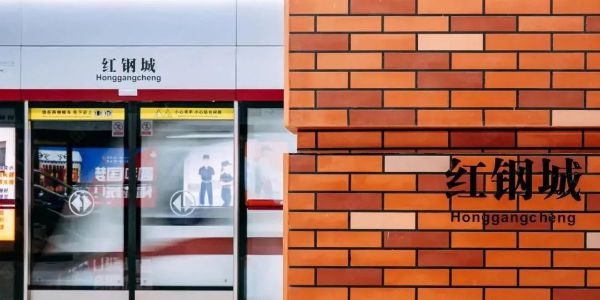
当地铁遇上宋体=铁宋
地铁,很多人每日出行的必备交通工具;宋体,生活中最常见的字体之一,然而它们的组合却不多见。但也正因为少,当地铁遇上宋体,反而就更加容易产生非常具有辨识度的效果。
如果到访过香港,乘搭过MTR,就很难不留意到各色磁砖墙、书法壁、标志性的「出」等MTR特色视觉符号,它们又与随处可见的宋体字相配合,形成了一套独特的风格。这些都源自于40多年前MTR设计部门的柯炽坚与同事一起设计的导视系统。
独特的MTR风格
香港地下铁路有限公司简称「地铁」,在两铁合并后改称「港铁」,这里统称「MTR」。1982年,MTR设计部门的柯炽坚与同事一起研究、制定出了指标规格、版型、各种标志,编写成为《香港地铁指标规范手册》,这套手册奠定了今日MTR风格的基础,同时也影响着学习香港的内地。而其中站牌的字体设计,在日后就被坊间称为「地铁宋」。
香港地铁指标规范手册(图源:梁佳KKKAI)
纵观全球,交通标识多采用无衬线体,毕竟它易认性更高。不过作为铁路的站内导向系统,其距离乘客更近,与步行乘客的相对速度也不高,因此可以稍稍提高风格化和观赏性的权重。柯炽坚与同事认为「地铁是城市精神的表征,而明体(即宋体)这个带有浓厚楷书基因的字体,用于站牌,才能彰显中华文化的气氛。」
黑体易认性高,被广泛应用于标识
武汉、南京、深圳等地的轨道交通也在部分场景使用过宋体,但MTR仍是少数以宋体作为主要导向用字的交通系统,但其自身也在一些地方转用其他宋体,一个原因是地铁通车后不久,柯炽坚便离开了MTR,地铁宋只完成了初期所需的数百字,笔画覆盖也不完整。此后虽然经过一些修改总共发展出了3版,但40多年来总体还是处于停滞状态。然而随着香港铁路的不断发展,地铁宋字库逐渐无法涵盖新站的需求。
武汉地铁站名使用了宋体
除了地铁宋,现在MTR较多使用的还有华康俪中宋,仔细观察2者,可能会觉得地铁宋有一些些「奇怪」,这是由于它参考了《康熙字典》等传统字典中的写法,例如「彩」的爪字头「爫」向外散,更似「爪」。
不同的「爫」
华康俪中宋更符合当代标准字形,「何文田」在站台和PIDS上的写法也能看出不同。
「文」区别明显
不过追溯俪宋的发展,它便是由柯炽坚在制作地铁宋的几年后完成并发展至今。柯炽坚也正因地铁宋而入行字体设计,因此对地铁宋也有一份特殊的情感。
没有地铁宋,也就不会有俪宋
于是今日已是资深字体设计师的柯炽坚,重拾这款改变他也融入整座城市生活的字体,命名为「铁宋」,制作成可以日常使用的字体。首先要做的是调整笔画、结构,毕竟40多年前字体新人柯炽坚及同事的作品,也有很多不成熟和需要改进的地方。
早期字形需要调整
让字体可被日常使用,另一点很重要的是补全字库,这不是一个小工程,常用汉字是早期地铁宋字库的是十倍甚至百倍。不单如此,这次计划将连简体也一并涵盖,让它可以像港铁风格一样走出香港。
东铁线站台的繁简俪宋
地铁融入了生活,铁宋也成为了城市不可或缺的记忆和元素。希望铁宋可以走出地铁,为人所知,也为人所用。